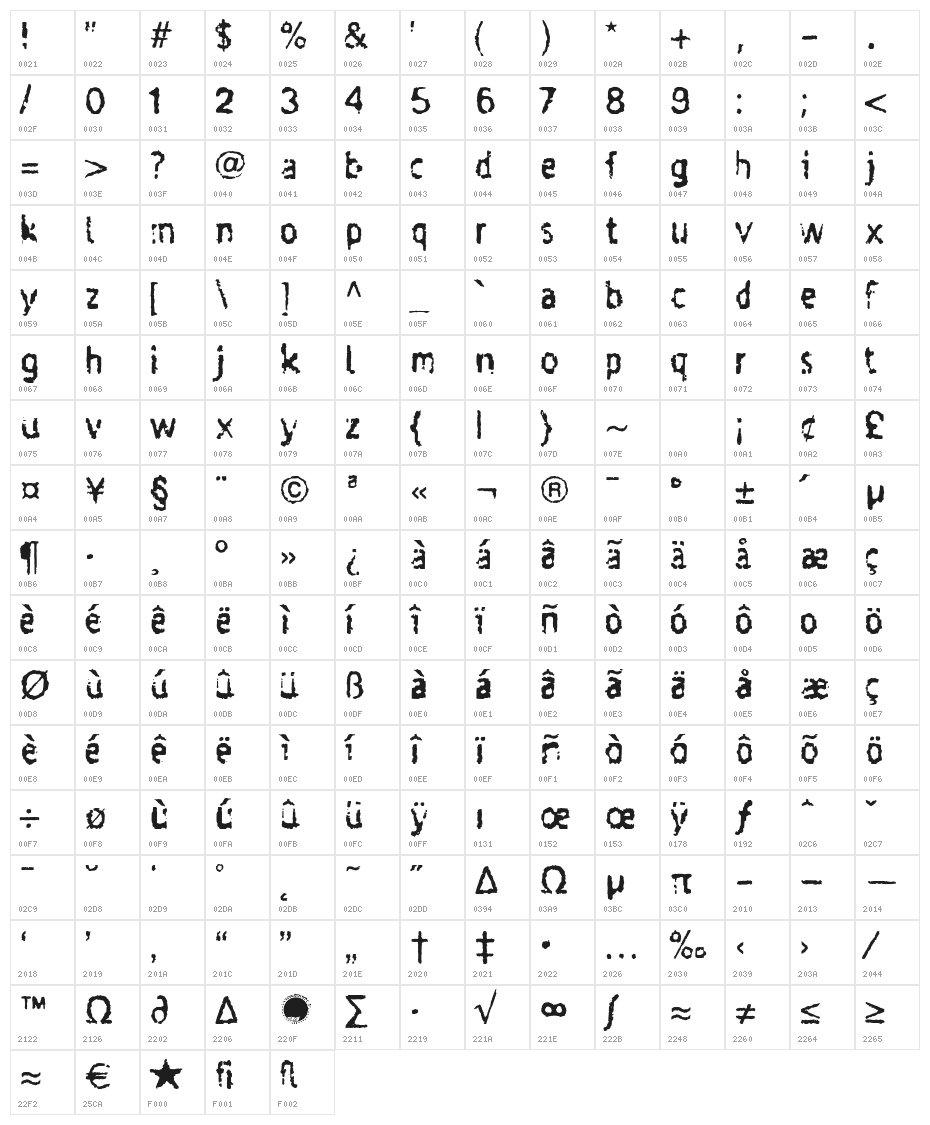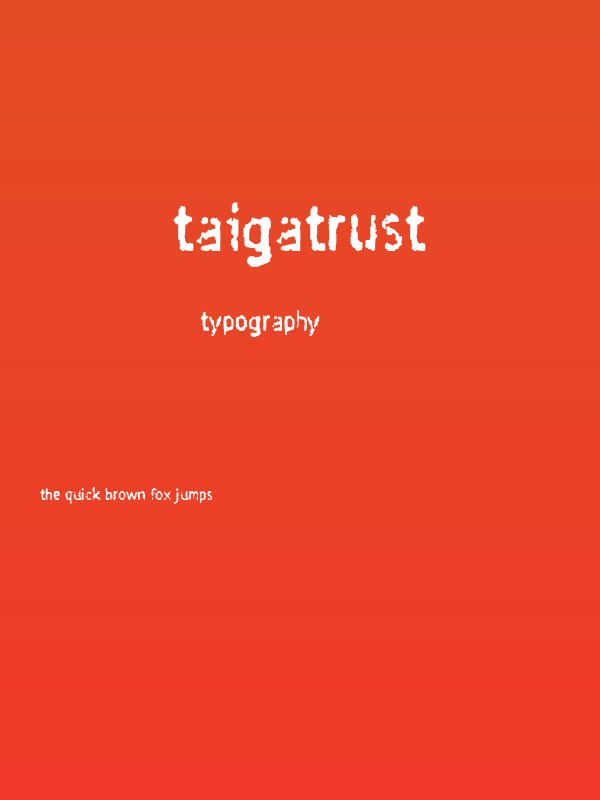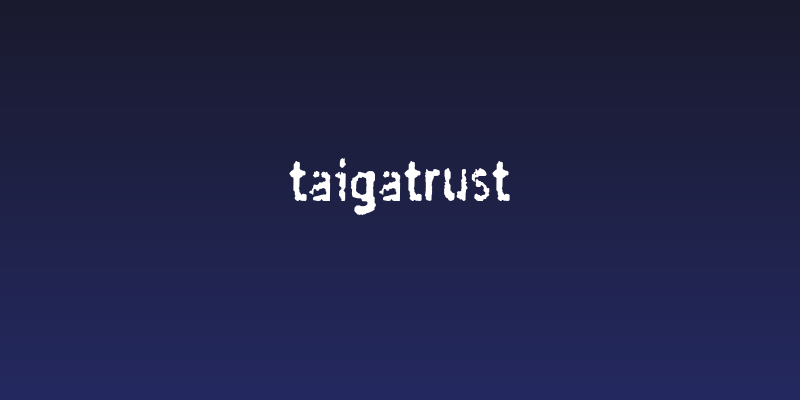
Taigatrust Font
| Stile generale | Rustic, Organic, Distressed |
| Progetti proposti | Ideal for branding, posters, album covers, and any design needing a rustic or natural vibe. |